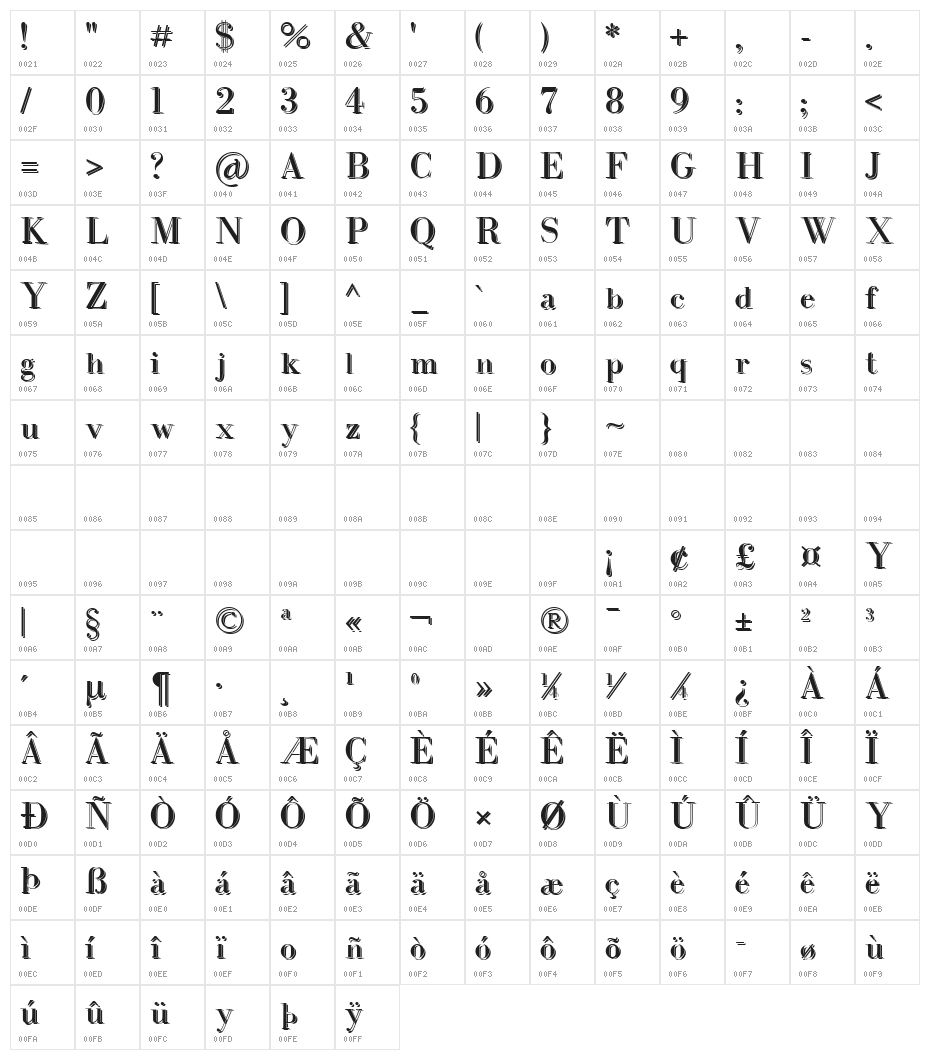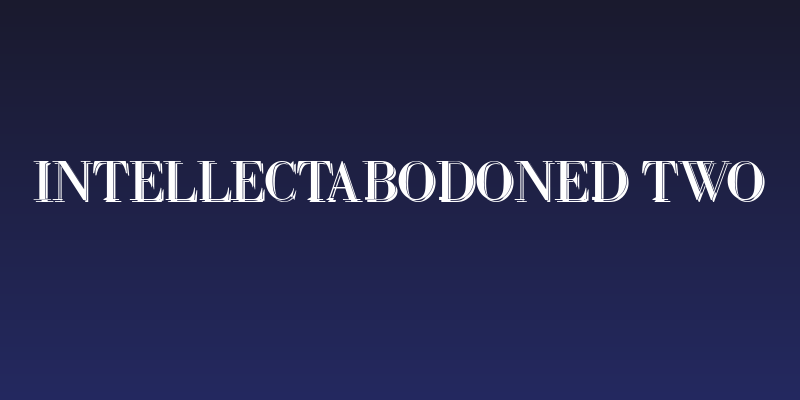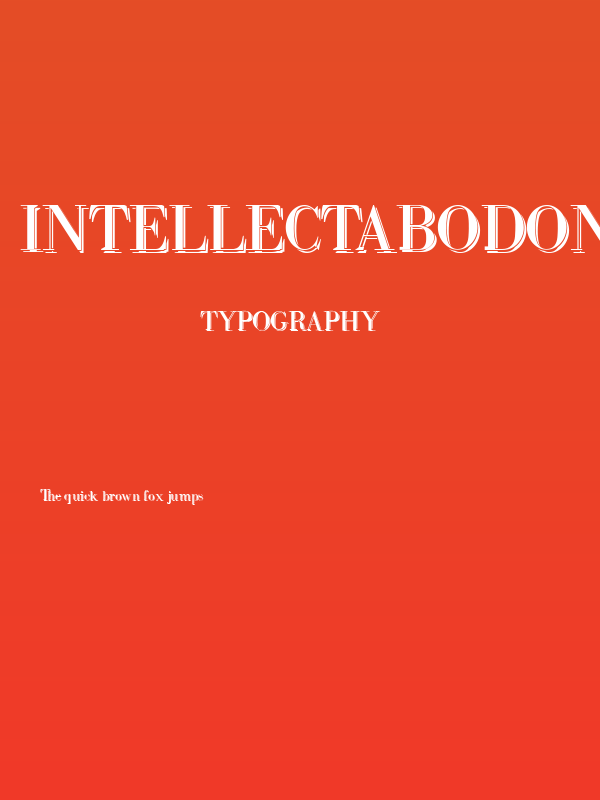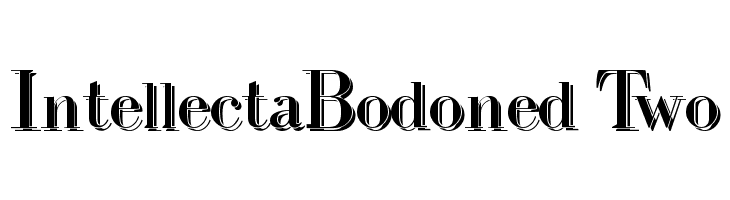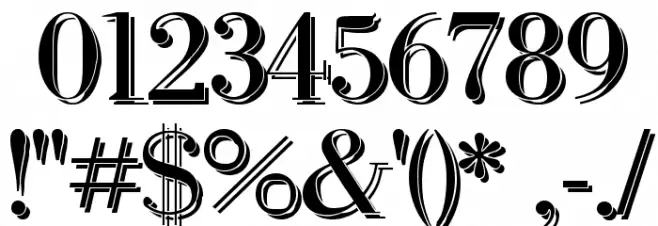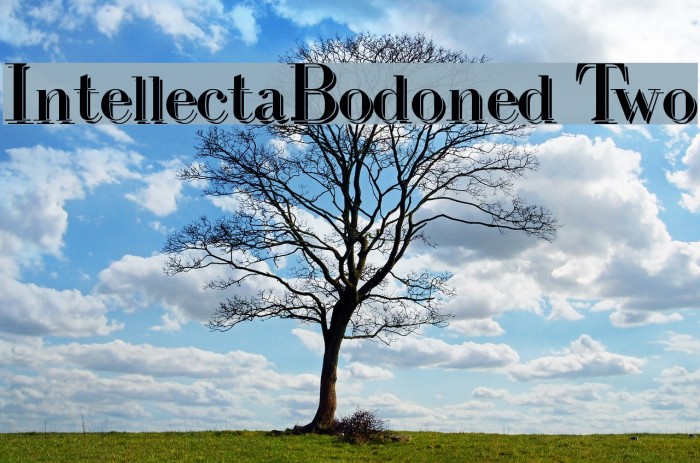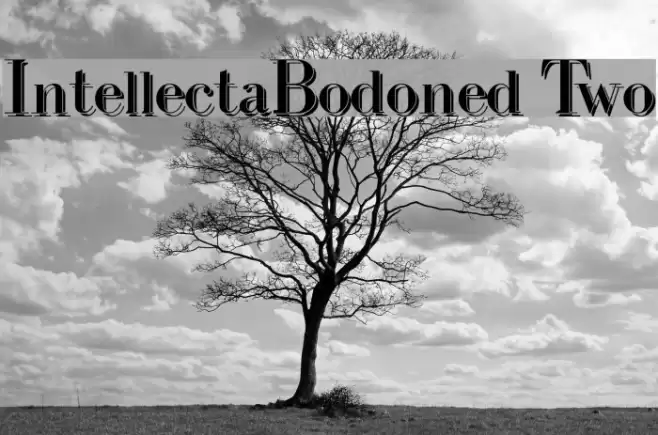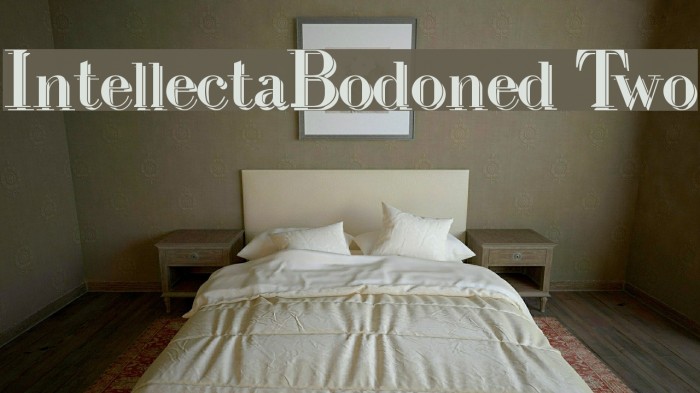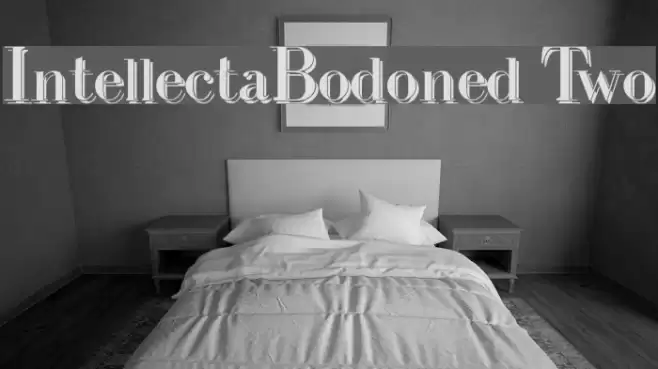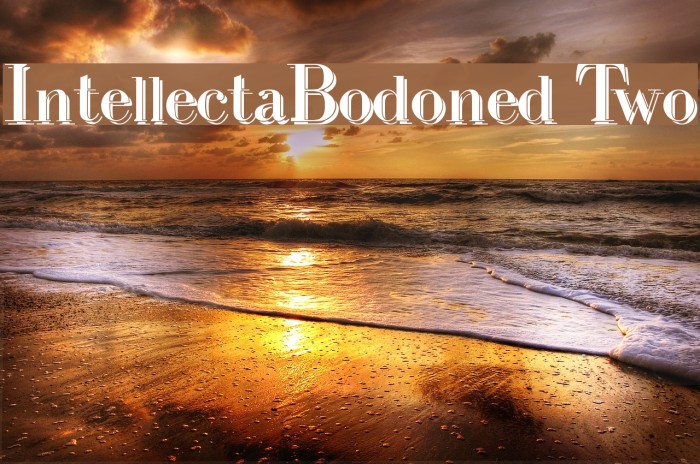
IntellectaBodoned Two Font
| Gesamtstil | Classic |
| Vorgeschlagene Projekte | Ideal for headlines, posters, branding, and editorial design where a strong visual impact is desired. |